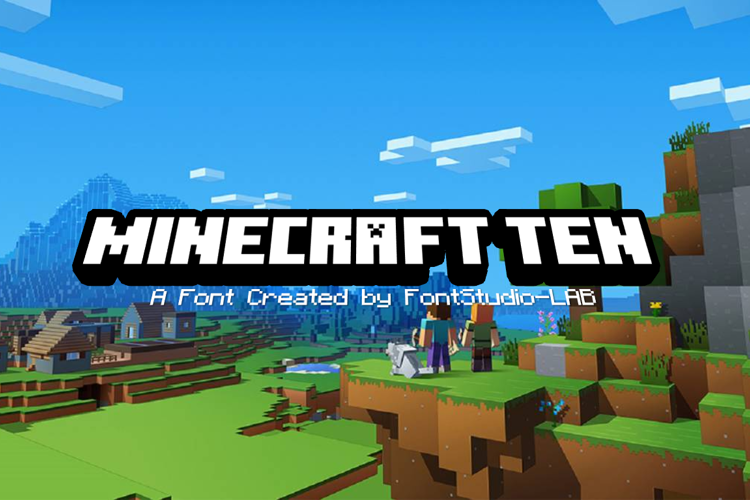
Minecraft Ten Font
Ten Style
Porfavor, usar "ƒ" para la letra A de minecraft así: MiNECRƒFT
there is no creeper in the A
Use "ƒ" for a Creeper in the A
How do you get the "f" key? I have tried symbols and everything I can think of. Por farvor, que es la letra "f"? Para la letra A en MINECRfFT???
@GGabrielGGames Use MiNECRƒFT For Full.
I FONT with the a is a creeper Crepper oh man